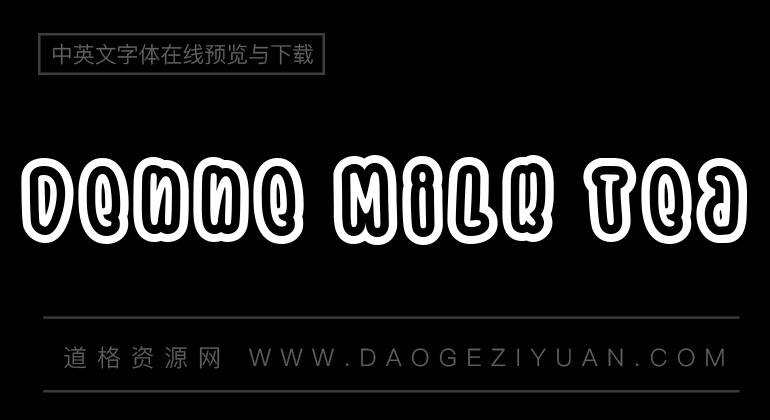
Denne Milk Tea
Denne Milk Tea 字体是一款简洁优雅的英文字体,由设计师Denne提供。它具有细节和精细的设计,以及优雅的曲线和精美的笔画。它具有良好的可读性和可识别性,适合用于大多数文字类型,特别是用于标题、标签、标题等。它还可以用于打印和网页设计,可以让您的设计更加有趣、精美和独特。
Denne Milk Tea是一款非常不错的手写艺术字体,具有很好的视觉感,适合于文化类的宣传设计、商业类品牌的广告和产品包装设计以及个性化文字排版等较多场景。
Denne Milk Tea字符映射图